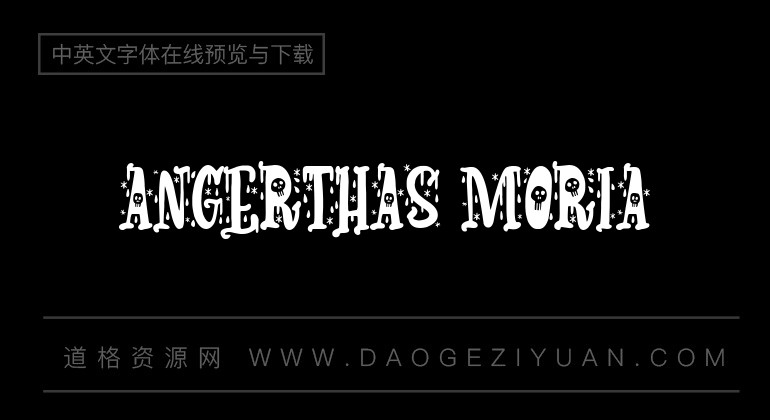
Angerthas Moria 是一款具有经典外观的英文字体,它受到《指环王》中的矮人语的启发而设计。它的字母和字形采用了精细的细节,并且拥有丰富的符号和记号,可以用于创建复杂的文字效果。Angerthas Moria 字体拥有英文和拉丁文字母,可以用于创建精美的文字效果。它也可以用于替代其他英文字体,以获得更加令人难忘的文字效果。内容介绍
Angerthas Moria是一款非常不错的手写艺术字体,具有很好的视觉感,适合于文化类的宣传设计、商业类品牌的广告和产品包装设计以及个性化文字排版等较多场景。